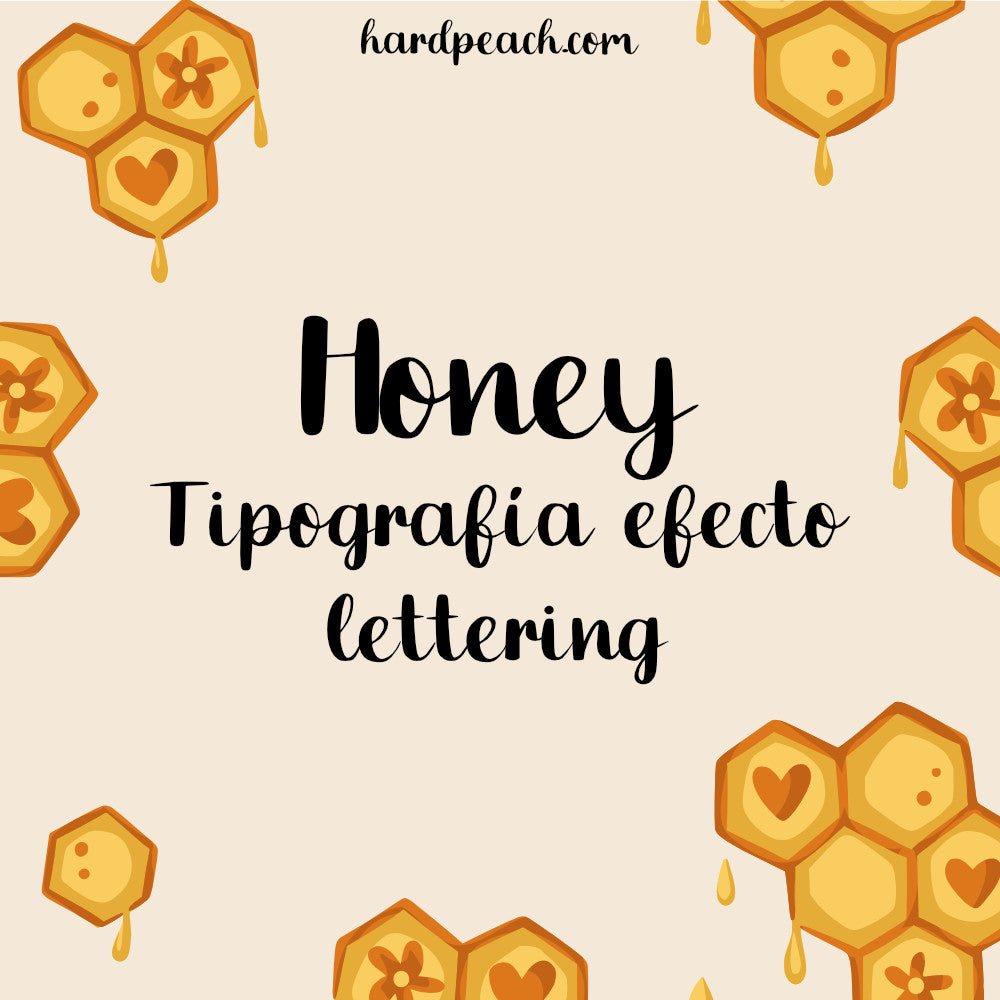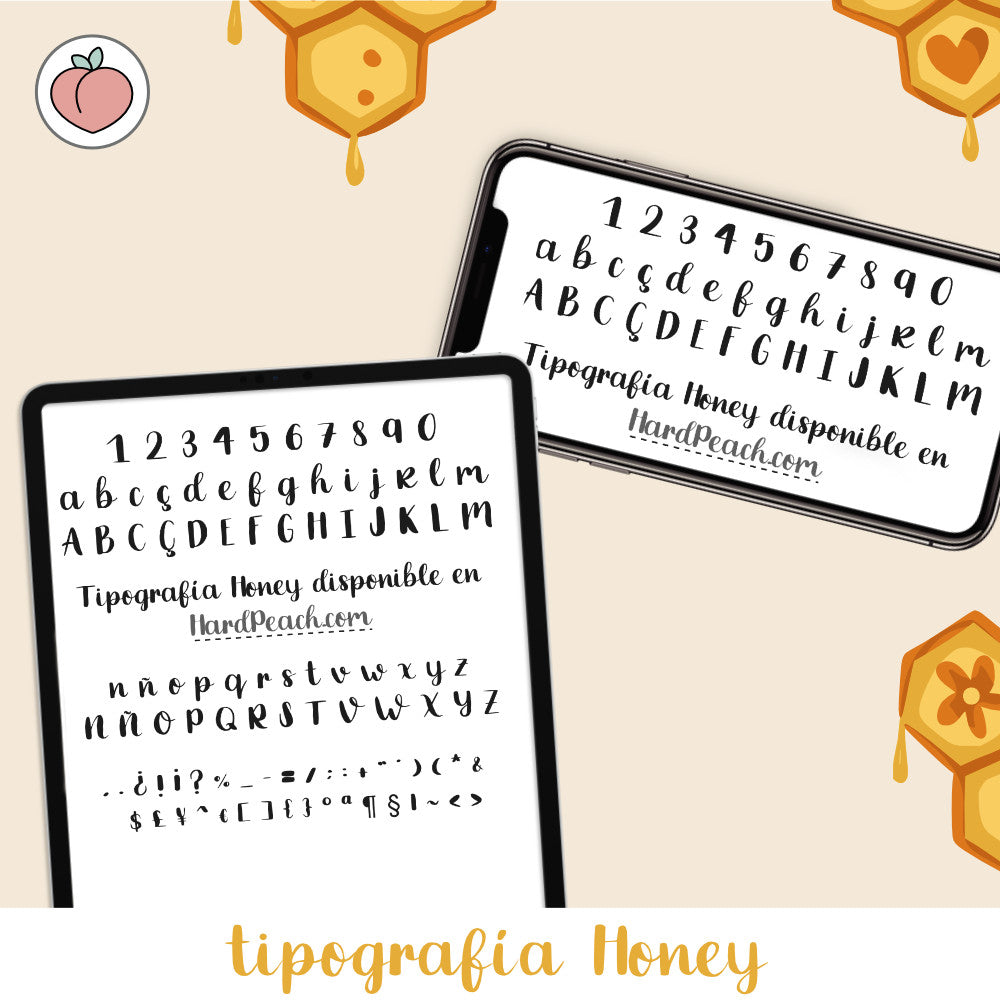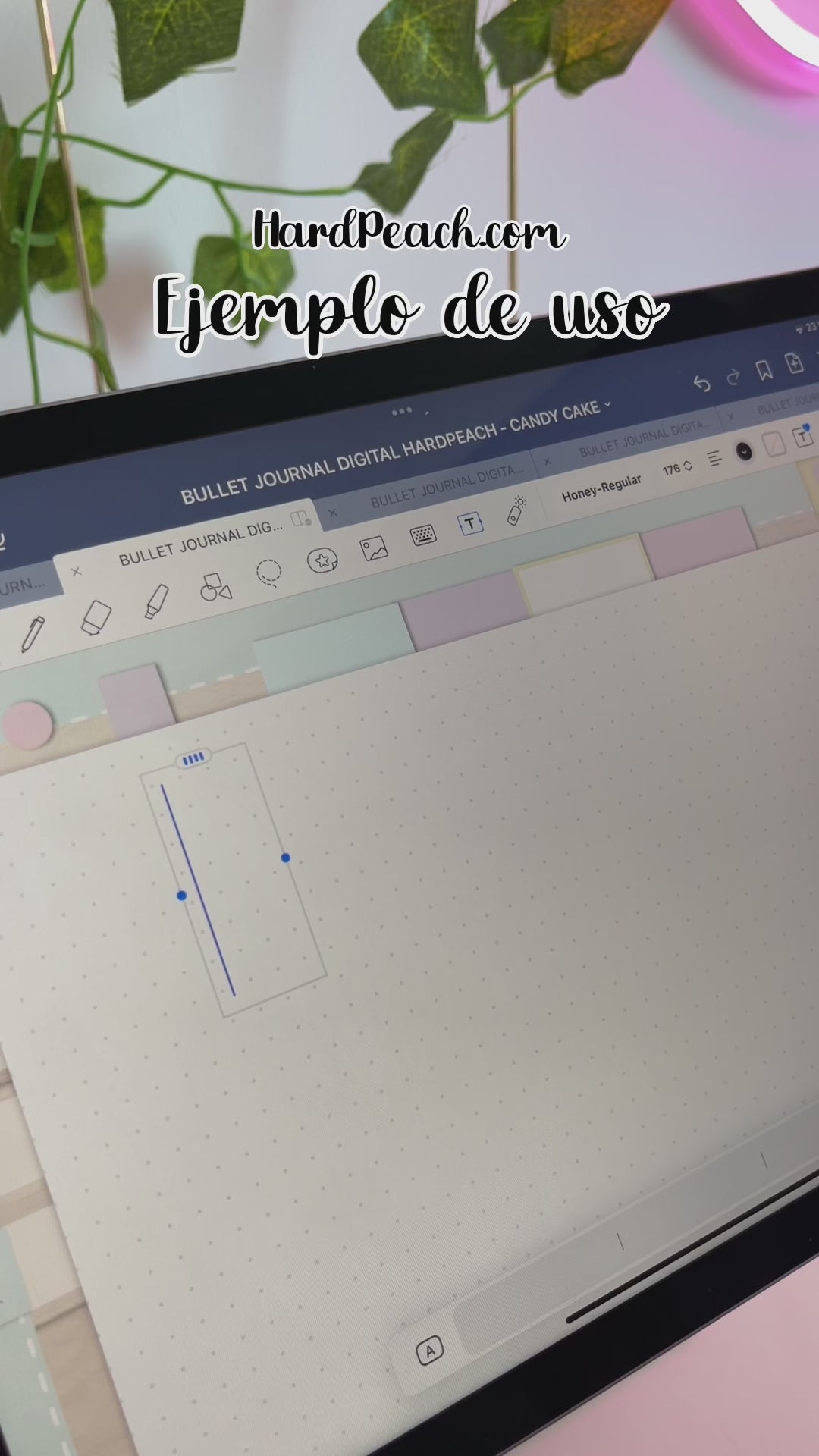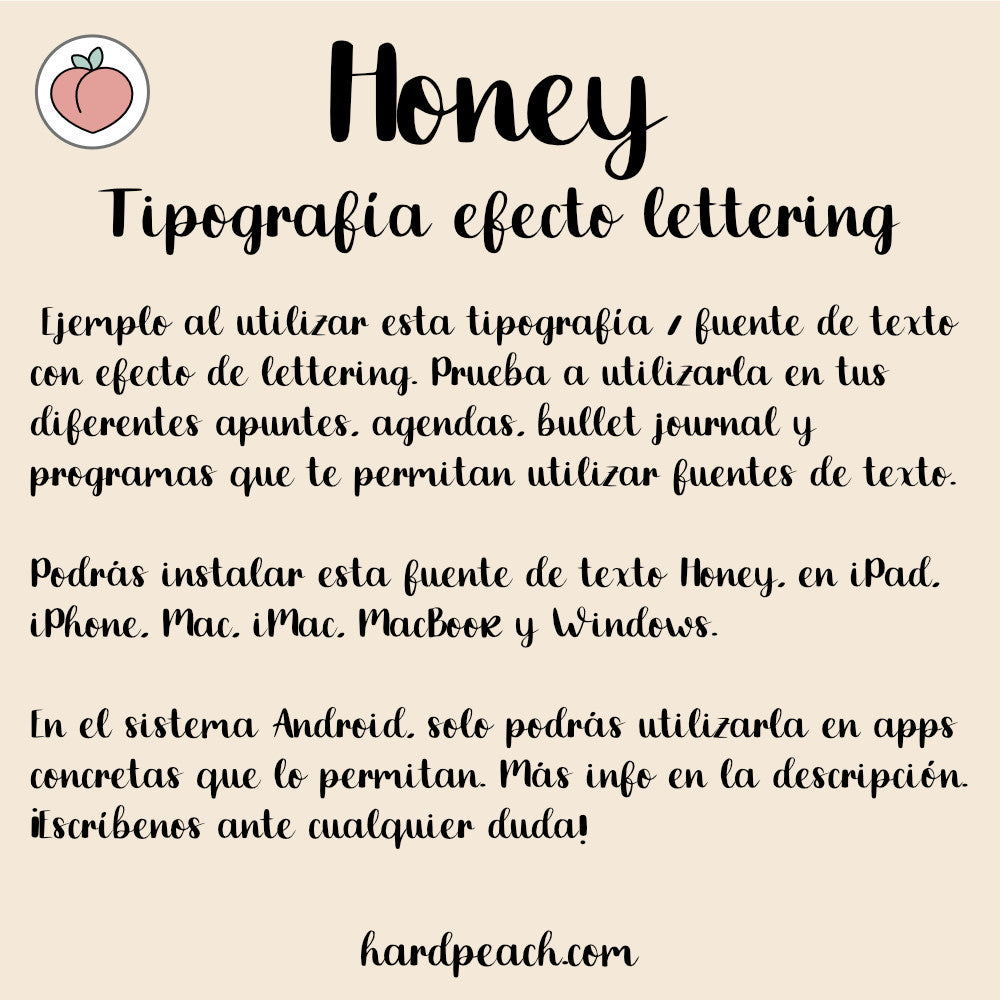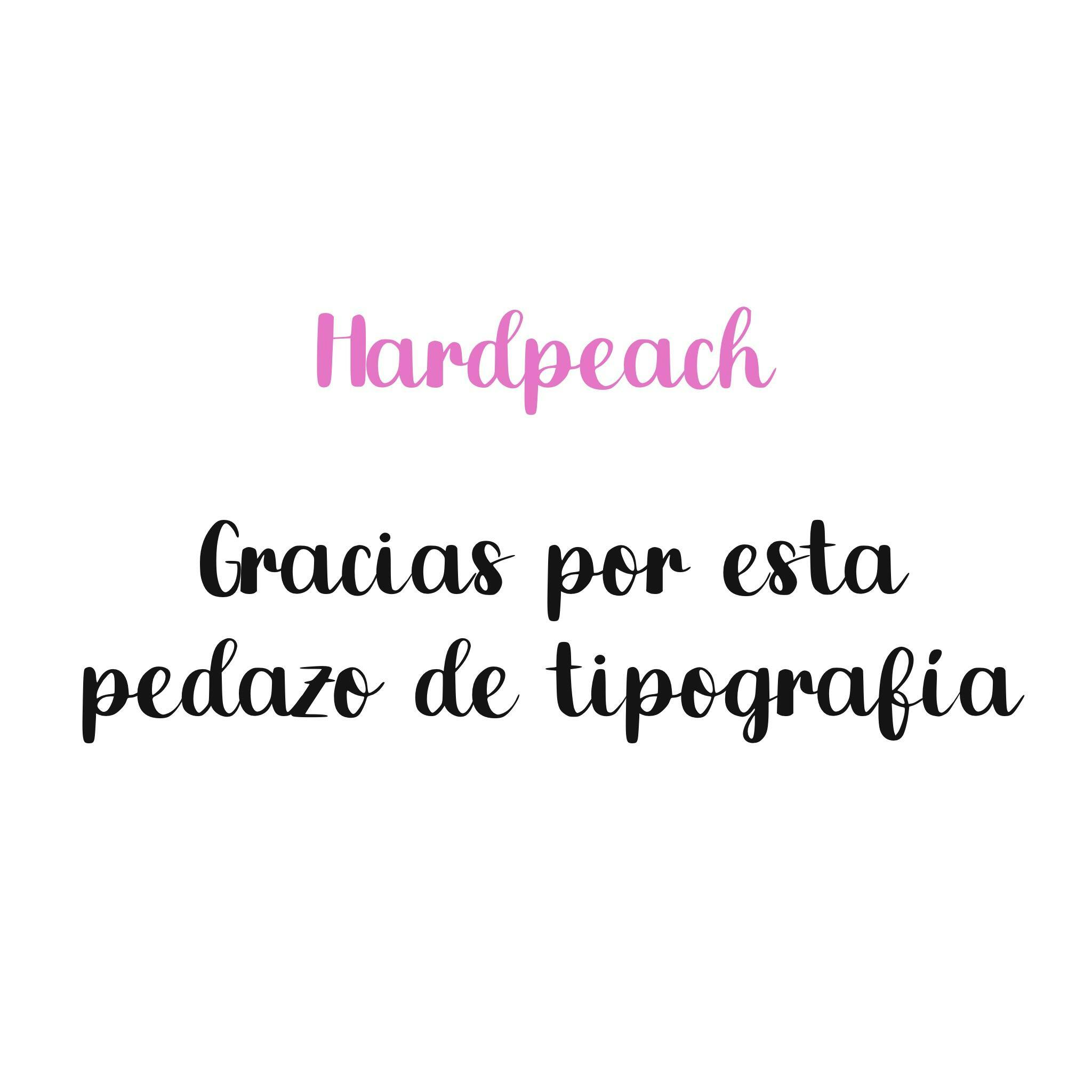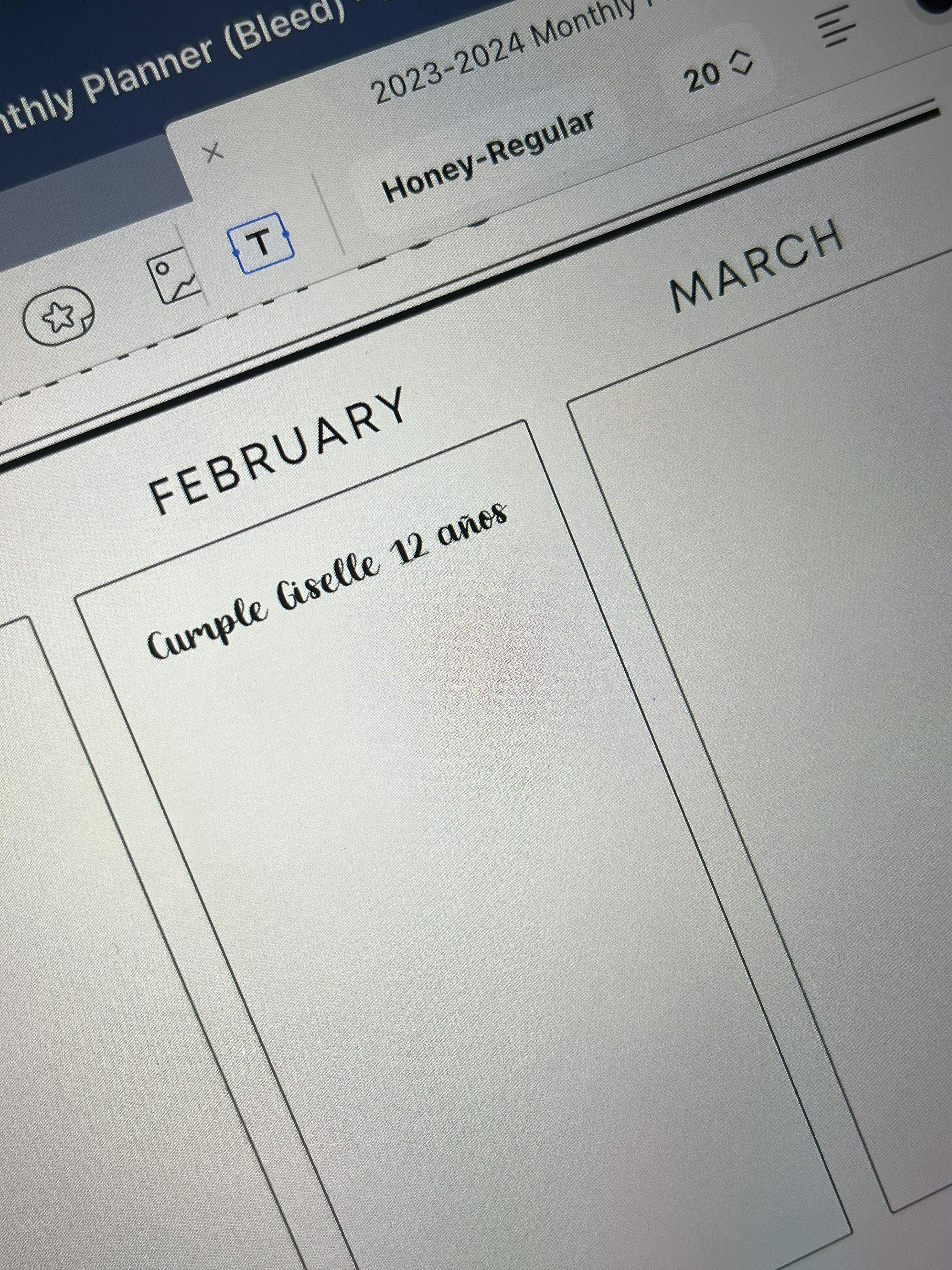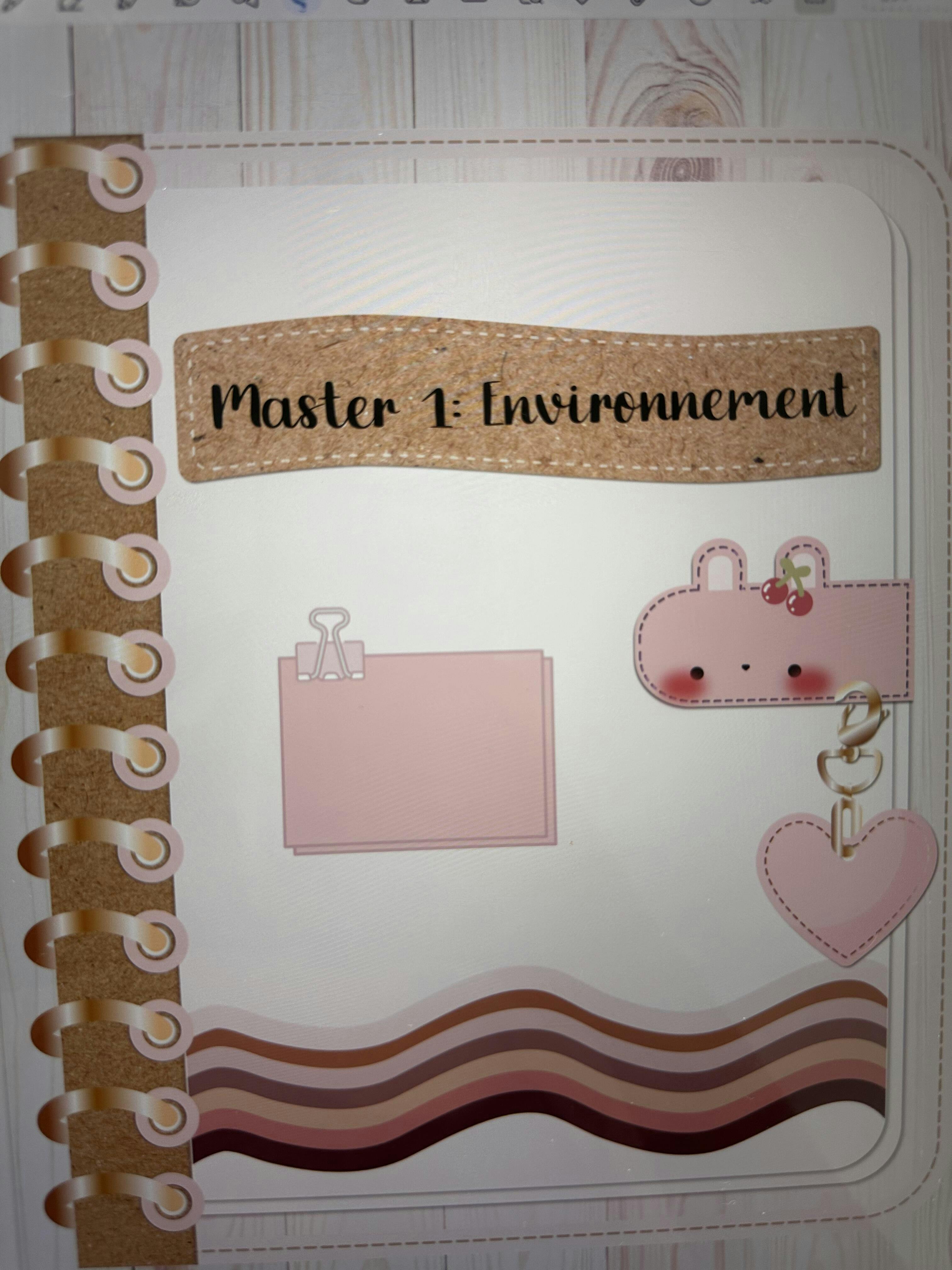
TIPOGRAFÍA LETTERING HONEY: fuente manuscrita para títulos con efecto lettering. Perfecta para apuntes, agendas, títulos y proyectos creativos
¡Lettering directamente desde tu teclado! ✨ Tipografía brush lettering para apuntes digitales, anotaciones y proyectos creativos.
Descubre nuestra tipografía Honey con efecto brush lettering, diseñada para que puedas escribir de manera elegante y creativa directamente con tu teclado, el teclado virtual de tu dispositivo o transformando tu letra manuscrita con Apple Pencil. Esta tipografía Honey de lettering digital es perfecta para apuntes digitales, notas, esquemas, diarios creativos, bullet journals, títulos, invitaciones y proyectos de ilustración o diseño.
Con esta tipografía puedes darle un estilo único y profesional a todos tus textos, personalizando colores, tamaños y estilos según tu proyecto. Es ideal para estudiantes, creativos, profesionales y cualquier persona que quiera hacer que sus apuntes digitales, planificadores, agendas o proyectos sean más atractivos y originales.
Ideas de utilización:
- Apuntes digitales, resúmenes y esquemas ✏️
- Bullet journals, agendas y diarios creativos 📖
- Invitaciones, carteles y tarjetas de felicitación 🎨
- Proyectos de ilustración y diseño gráfico 🖌️
- Títulos llamativos para presentaciones y documentos 📑
Convierte tus notas, agendas, diarios o proyectos creativos en algo profesional, único y original con esta tipografía estilo lettering. Expresa tu creatividad, personaliza tus textos y haz que tus apuntes digitales y proyectos brillen con un estilo totalmente moderno y artístico.
La tipografía de lettering Honey incluye todos los caracteres principales, mayúsculas, minúsculas, números, vocales con tildes (español), y acentuaciones abiertas (à) y signos. Además, incluye la acentuaciones y las letras ñ y ç.